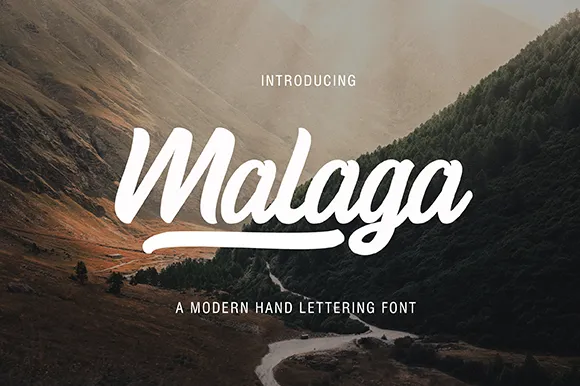
Malaga Script Font – Download Grátis
Descubra a beleza única e moderna da Malaga Script Font, uma escolha perfeita para quem busca expressar personalidade com elegância. Inspirada na caligrafia elaborada, esta fonte mistura seu estilo leve e descontraído para criar um tipo de fonte fresco e divertido que se destaca em várias aplicações. A Malaga é uma escolha legível, ideal para projetos variados e práticos. Esta fonte vem com opções alternativas, o que torna ainda mais versátil seu uso tanto no design editorial quanto na criação de marcas digitais ou gráficos. Com um toque de alegria e uma dose saudável de simplicidade, a Malaga é perfeita para aqueles que desejam adicionar um toque único à sua arte digital.